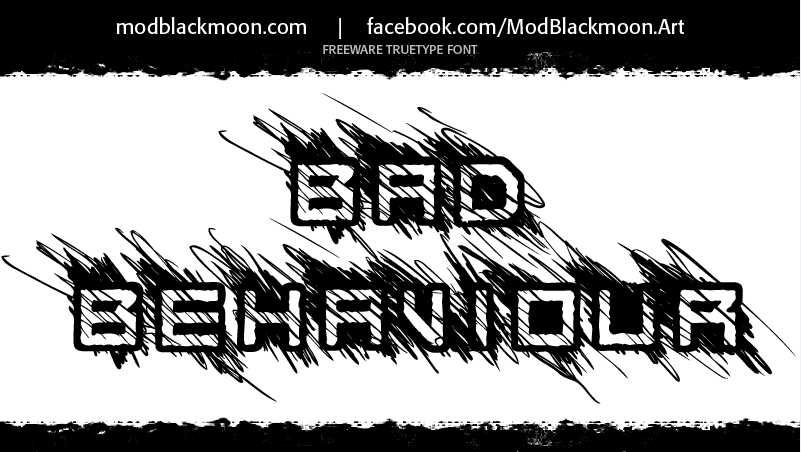
A “Bad Behaviour” é uma fonte symbol criada pelo designer Hamilton que apresenta uma aparência enigmática e urbana, como se fossem digitos inscritos em grafite na cidade. Sua influência gótica e a sensação de vandalismo bruto remetem diretamente ao estilo do crime organizado, o que lhe dá um ar intrigante que chama à atenção. A fonte inclui letras inglesas, europeias, números e sinais de pontuação básicos, criando uma ferramenta versátil para textos digitais urbanos ou qualquer aplicação visual em estilo grunge. Desenvolvida em agosto de 2015, esta font é gratuita tanto para uso pessoal quanto comercial, um benefício adicional para designers e entusiastas do design que buscam uma ferramenta única no seu arsenal. Foi validada pela fontes de ligação hierárquica de caracteres (HLFC) sem nenhum erro, garantindo a precisão e consistência esperadas em qualquer aplicação visual.